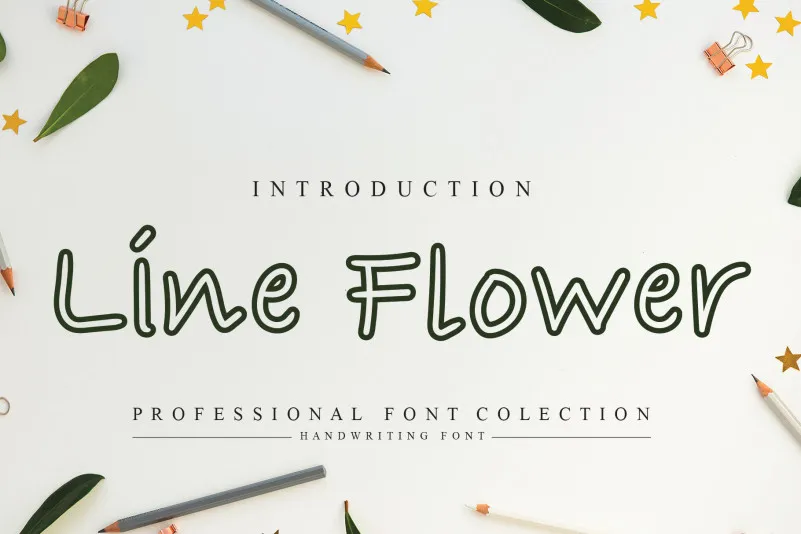
A fonte ‘Line Flower Display Font’ apresenta-se como uma elegante e amigável escolha para desenhos manuscritos. Com suas linhas retas e formas suaves, essa fonte é perfeitamente adaptada para os designs informais que buscam um toque relaxado e casual. É ideal para aqueles que procuram uma fonte de escrita livre para projetos pessoais ou DIY, oferecendo o equilíbrio entre praticidade e estilo. O designer andikastudio criou esta fonte com sabedoria, resultando em um recurso gráfico perfeito para quem busca uma combinação única de simplicidade e charme na sua próxima criação visual.